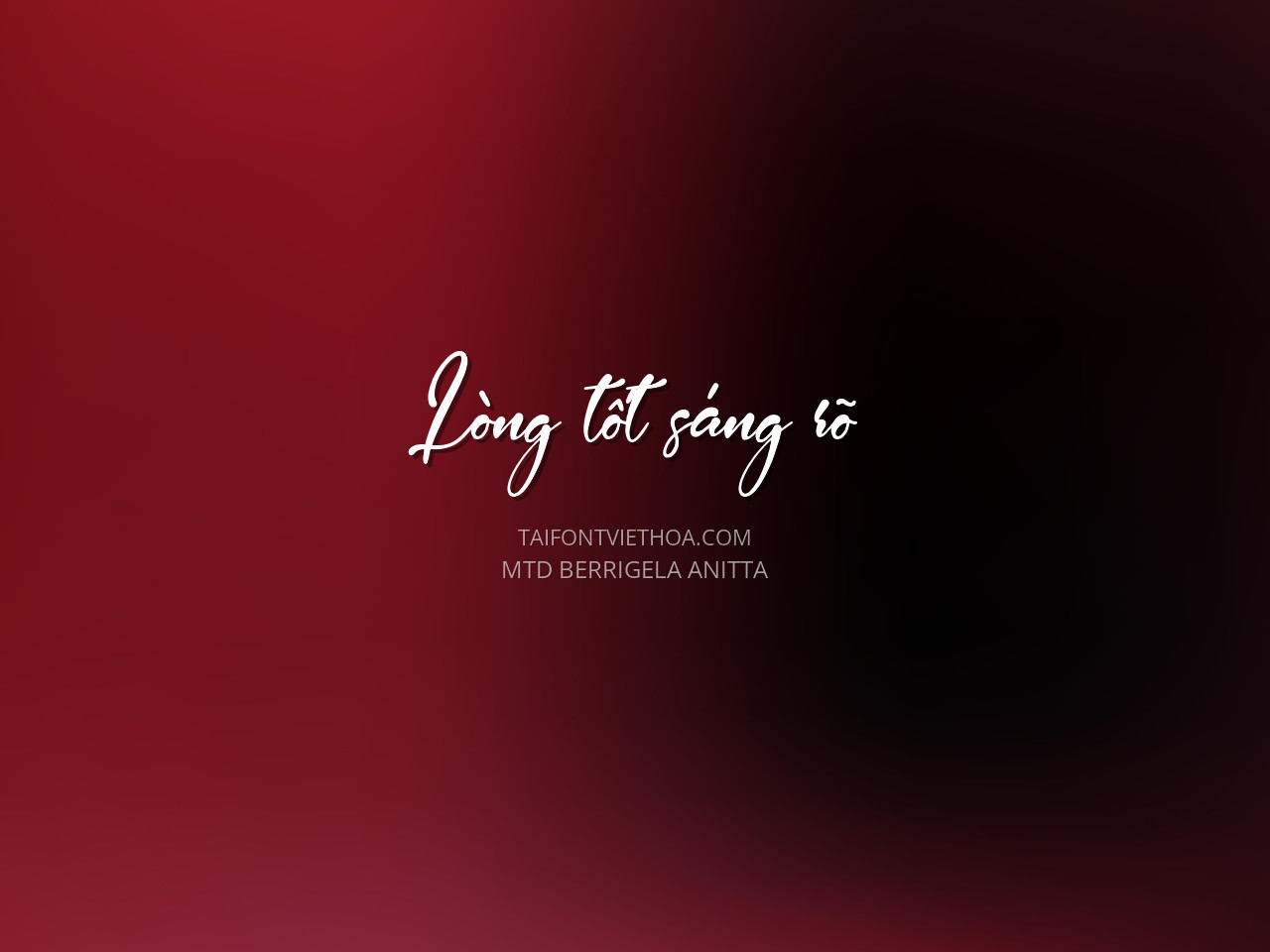
Font việt hóa MTD Berrigela Anitta
Giới thiệu về font Berrigela Anitta – Mềm mại, nữ tính và đầy cảm xúc viết tay
Berrigela Anitta là một kiểu chữ viết tay (handwritten script) mang phong cách hiện đại, nhẹ nhàng và tinh tế. Font được thiết kế với mục tiêu tạo cảm giác gần gũi như một nét bút tay uyển chuyển trên giấy, rất thích hợp cho các dự án cần sự dịu dàng, nữ tính và lãng mạn. Với các nét chữ mềm, nối liền mạch và form cong tròn duyên dáng, Berrigela Anitta thường xuất hiện trong thiết kế thiệp cưới, bao bì mỹ phẩm, logo thương hiệu cá nhân hoặc các ấn phẩm handmade. Font hỗ trợ hệ ký tự Latin mở rộng và hơn 60 ngôn ngữ quốc tế.
Phiên bản Việt hóa do Mộc Hạthực hiện đã bổ sung đầy đủ bộ dấu tiếng Việt, đảm bảo khả năng ứng dụng mượt mà trong thiết kế tại thị trường Việt Nam. Taifontviethoa.comđã chọn lọc và chia sẻ font này như một công cụ thiết kế lý tưởng cho các dự án cần sự tinh tế, cảm xúc và cá nhân hóa cao, đặc biệt là trong lĩnh vực làm đẹp, sự kiện hoặc thương hiệu nữ tính.
Đặc điểm thiết kế nhẹ nhàng và ứng dụng lý tưởng của Berrigela Anitta
Font Berrigela Anitta có đường nét tròn trịa, nghiêng nhẹ và các ký tự kết nối linh hoạt, mô phỏng nét viết tay tự nhiên nhưng vẫn rõ ràng, dễ đọc. Font đi kèm nhiều swash (đuôi trang trí), ligatures và ký tự thay thế (alternates), giúp người dùng sáng tạo bố cục chữ đẹp mắt, mềm mại và mang tính nghệ thuật cao. Đây là kiểu font lý tưởng để làm nổi bật thông điệp cảm xúc hoặc thể hiện phong cách riêng của thương hiệu.
Font phù hợp với các thiết kế như: thiệp cưới, thư mời sự kiện, logo mỹ phẩm, thương hiệu spa, trích dẫn nghệ thuật, blog cá nhân hoặc bao bì sản phẩm thủ công. Ngành nghề lý tưởng gồm: tổ chức sự kiện, thiệp cưới – ảnh cưới, mỹ phẩm thiên nhiên, thời trang nữ, spa – làm đẹp, sản phẩm handmade hoặc các thương hiệu cần sự bay bổng, mềm mại và cảm xúc trong truyền thông.